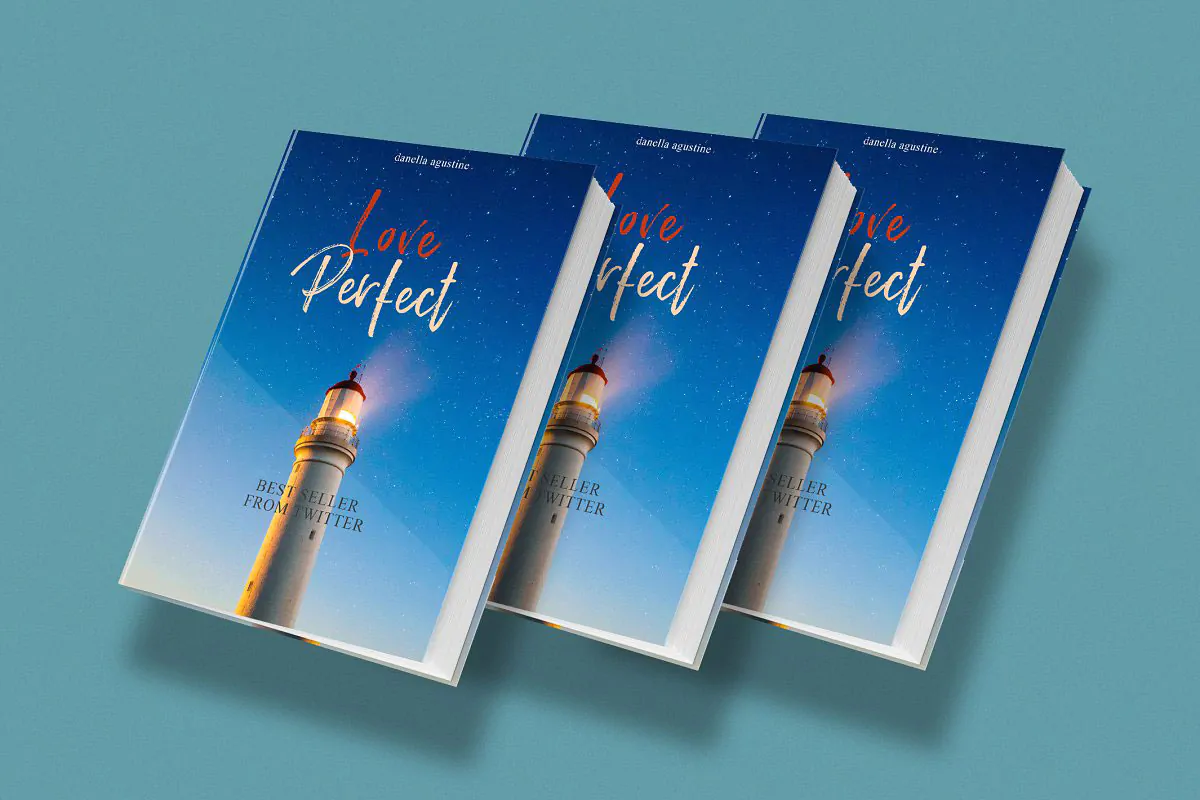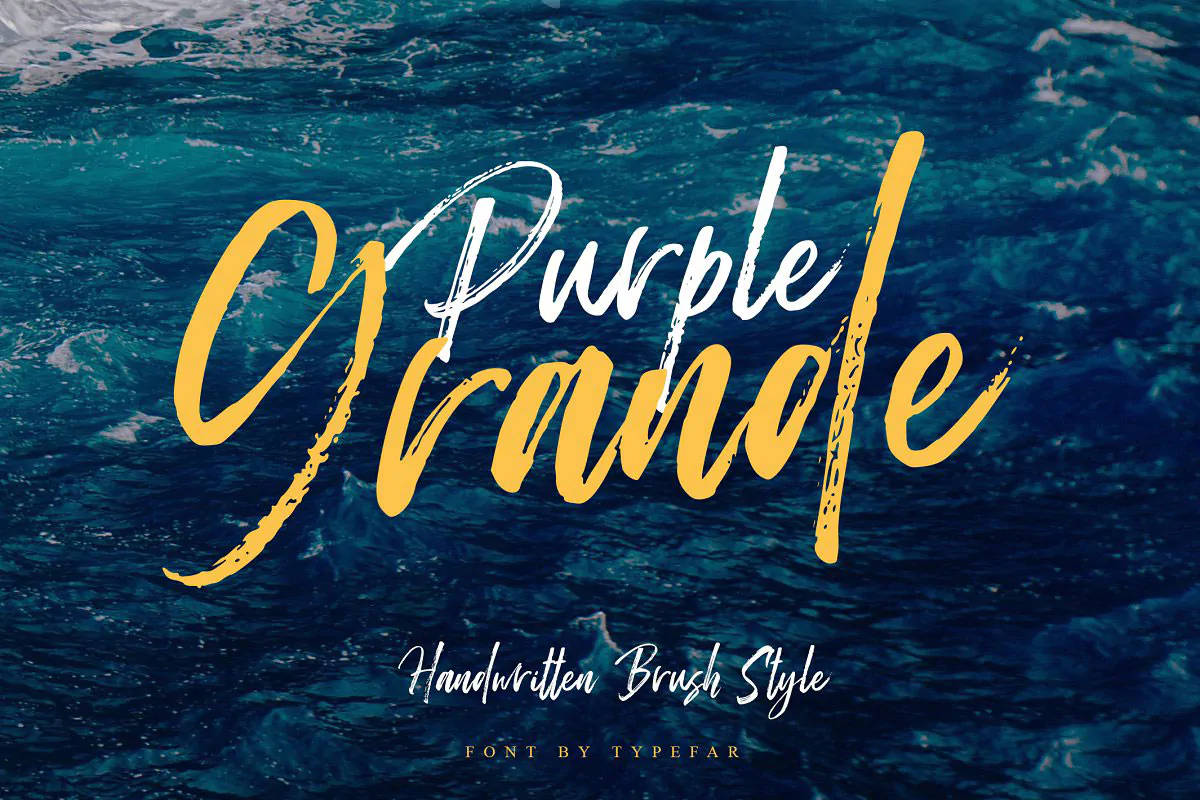
اسکریپت فونت قلمویی Purple Grande یک قلم فوق العاده زیبای انگلیسی است که به سبک رنگ قلمو طراحی شده است و مناسب برای استفاده در طرح و پروژههای گرافیکی مختلف میباشد.